100多款精美免费的英文设计字体素材下载 - 年度精选合集打包 (第二部分)
这些英文设计字体都非常适合用于制作 Logo、Banner 等,并且它们都是免费的,相信你一定不会错过!和上一部分一样,这些英文字体都是2012年度发布的,可以看作是12的年度免费英文字体合集了。这次废话就不多说了,希望这个合集能对你有所帮助吧!赶紧下载收藏哦亲……
免费英文设计字体预览图:
Stroke
Prosto
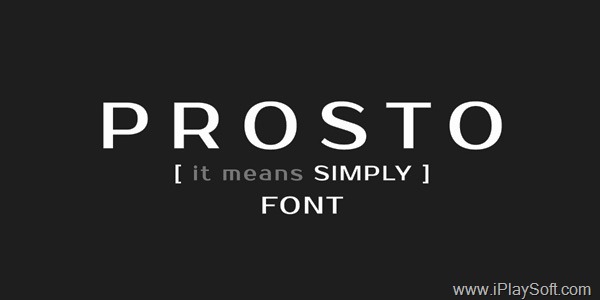
Jura
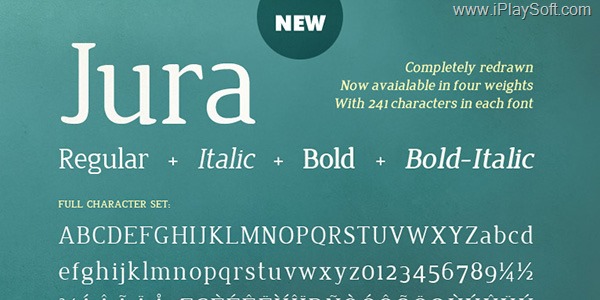
Akashi
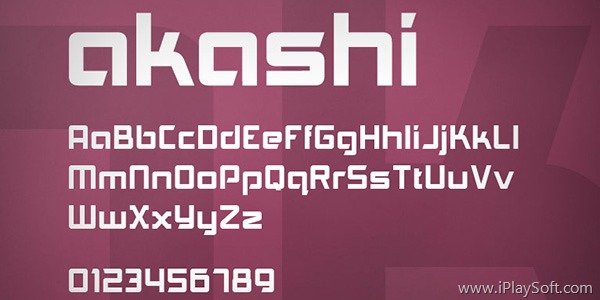
Source Sans Pro
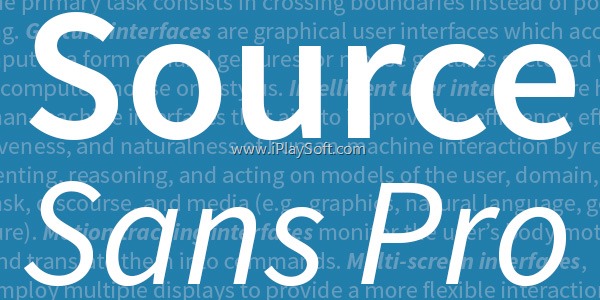
Flex Display
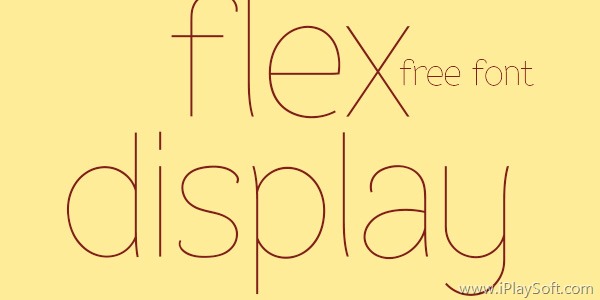
Valentina
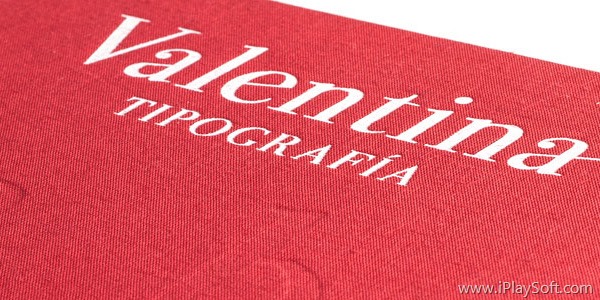
Poly
Noticia Text
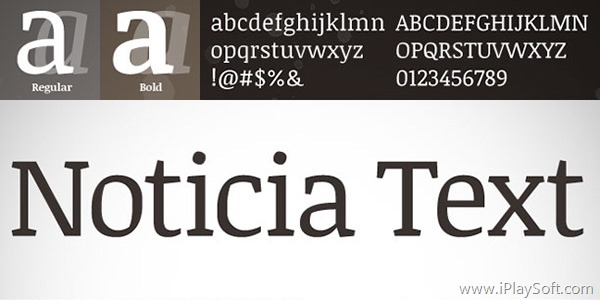
Jockey
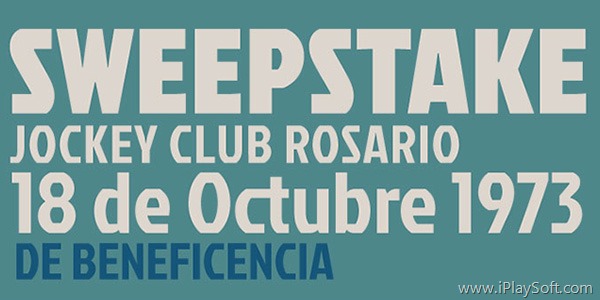
Bree Serif
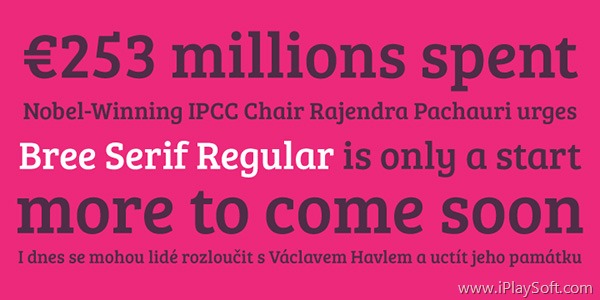
Hagin
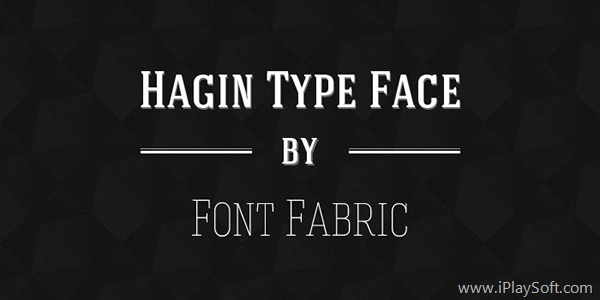
Prociono
Abril Fatface
Adelle
Intro
Cabin
Archive
Exo
Banda
Novecento sans
Static
Rex
47 - Typeface
Musket
Corporata
Acorn
Cosmo Path Type
Uralita
Pilaca
Alphageometry
Hagin Serif
Deco Neue
Sofia Pro
Jenna Sue
Tetra
Stiff Staff
PLSTK
Adec2.0
Corki
Piron
Glide
Ananda Namaste
Deftone Stylus
AleksandraC Vintage
Teléfono